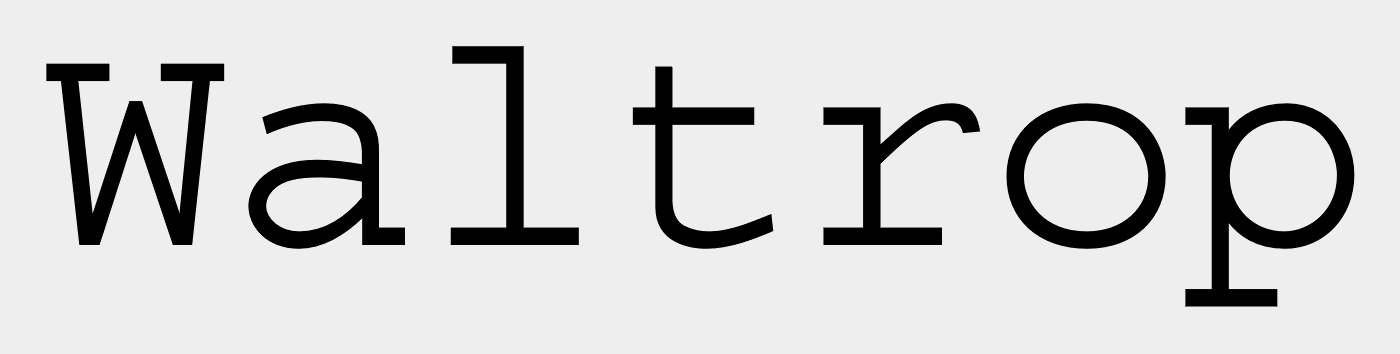
Welche Schriftart (Waltrop)
Hallo, vielleicht kann mir jemand helfen, welche Schriftart ist da? Danke ( siehe Anhang )
Courier, hier höchstwahrscheinlich die "Courier Std" von Adobe (waagerechte Serife am d)